Für modernes Design steht Helvetica wie kaum eine andere Schriftart – klar, schnörkellos und zeitlos. Doch wer auf der Suche nach Alternativen oder Alternativvarianten ist, findet in diesem Beitrag 22 hochwertige Fonts, die das typografische Erbe von Helvetica fortführen. Ob Branding, Webdesign oder Editorial – diese Schriften verleihen deinem Projekt Struktur und Eleganz.
Geschichte
Helvetica, entwickelt 1957 von Max Miedinger, besticht durch ihre neutrale Form und geometrische Klarheit. Sie wurde schnell zur Standard-Schrift der modernen Ära – insbesondere im Corporate-Design und öffentlichen Raum. Ihr Einfluss zeigt sich bis heute in zahlreichen Grotesk‑Schriften, die Helvetica‑ähnlich, aber mit eigenen Charakterzügen gestaltet sind.
Trend
Im Jahr 2025 erleben wir ein Revival der klaren Grotesk‑Ästhetik. Designer setzen gezielt auf moderne Sans‑Serif‑Schriften, um zeitgemäße Markenbilder zu schaffen. Ob digital oder print, diese Fonts bieten maximale Lesbarkeit und Understatement gleichermaßen – gerade in minimalistischen Layouts sind sie unentbehrlich.
Font‑Empfehlungen
1. Acello – Geometric Sans Serif
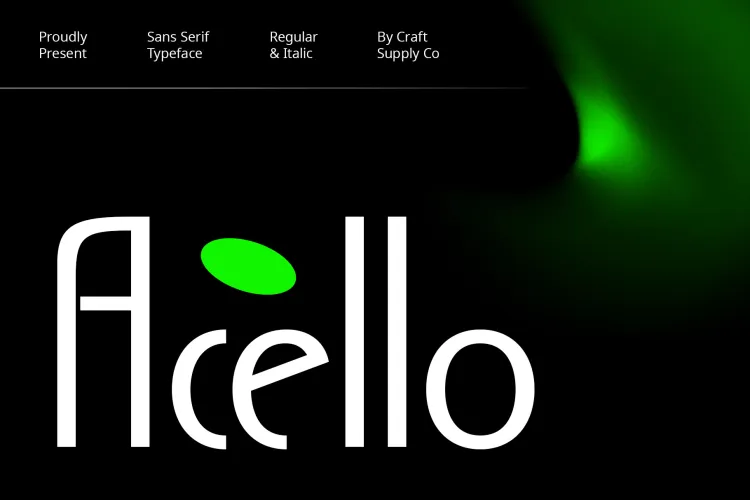
Minimalistisch und modern – klare Kreisformen und reduzierter Look.
2. Arnel – Bold Sans Serif
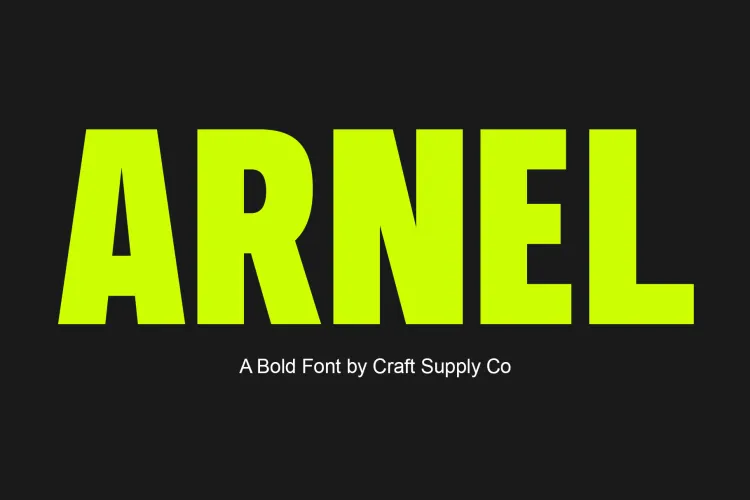
Starke Präsenz, ideal für plakative Headlines.
3. Bergins – Grotesque Sans Serif
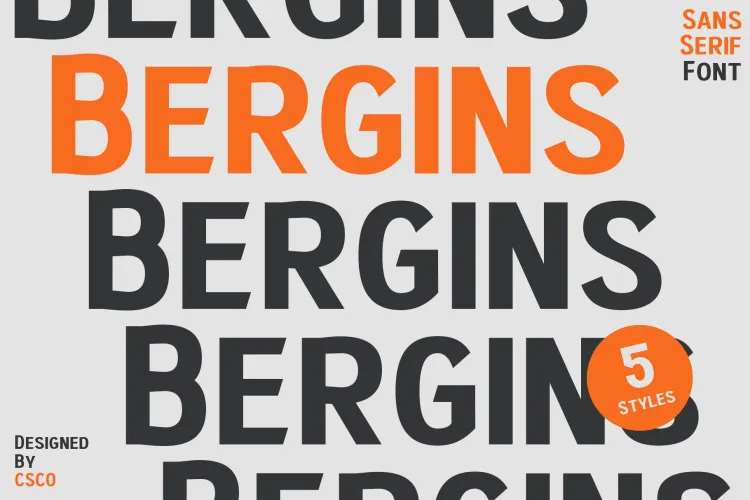
Retro-Anklänge mit zeitgemäßem Twist – vielseitig einsetzbar.
4. Blonden – Condensed Sans Serif
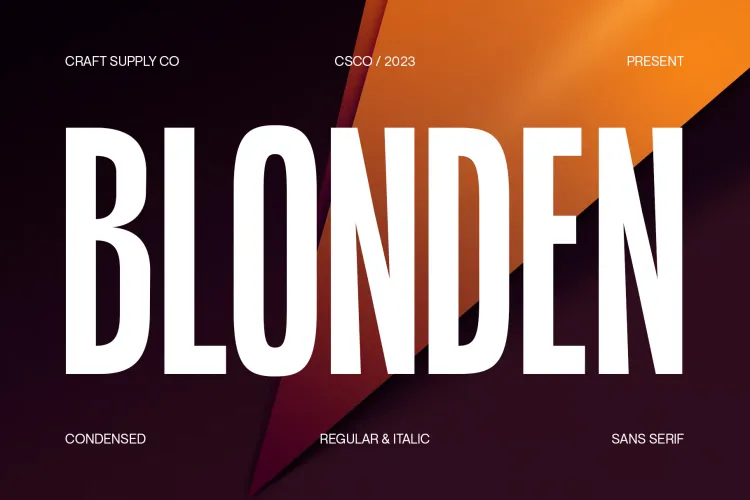
Schmal und elegant – perfekt bei wenig Platz.
5. Bondie – Condensed Sans Serif
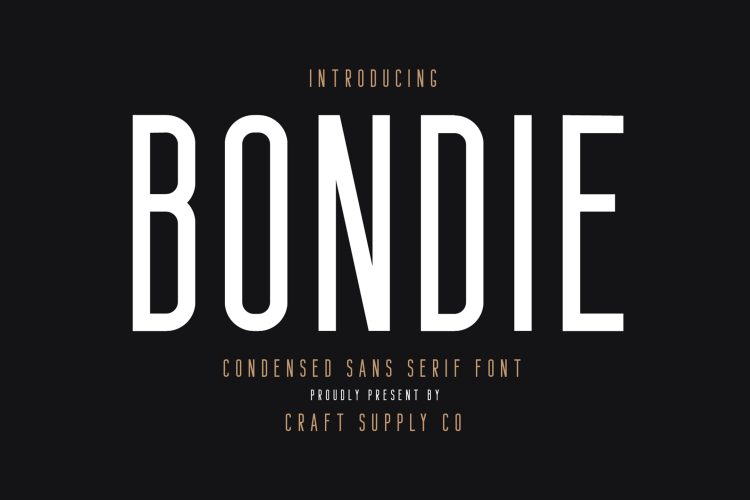
Klare Linien, optimierte Lesbarkeit – ein echter Allrounder.
6. Campeno – Geometric Sans Serif
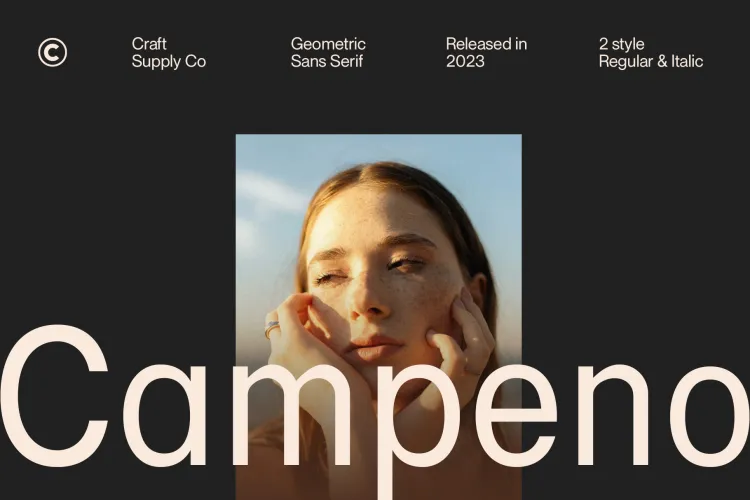
Geometrischer Charme mit moderner Note.
7. Cenios – Expanded Sans Serif
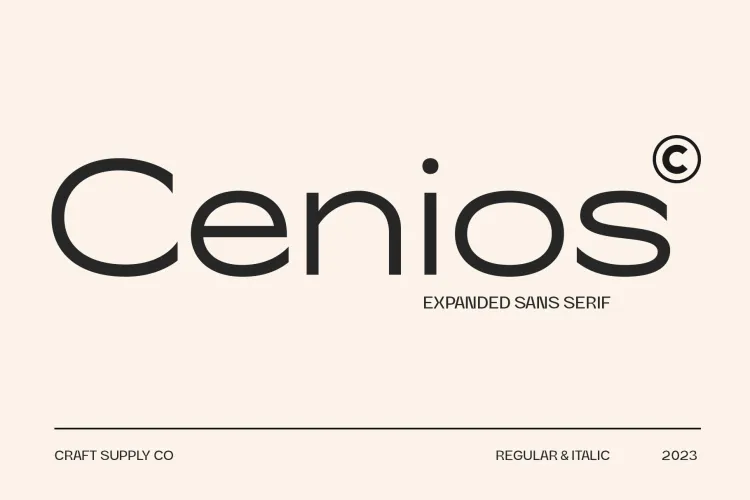
Weitläufiger Font mit großem Auftritt.
8. Corwine – Modern Font
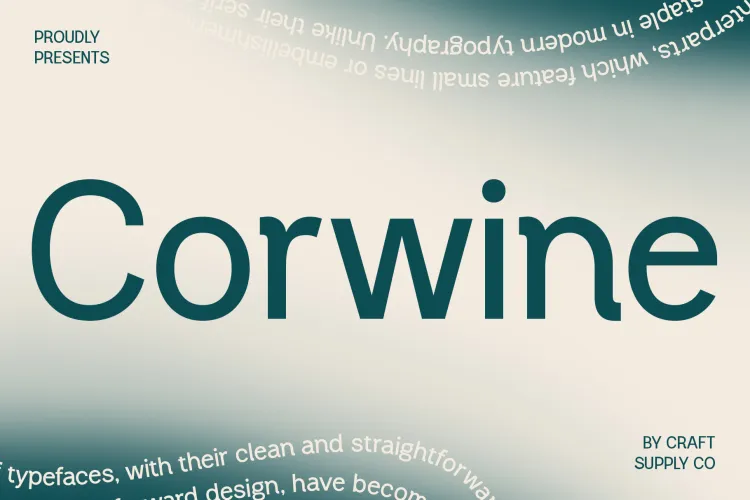
Neutraler Charakter mit zeitlosem Flair.
9. CS Margiela – Contemporary Font
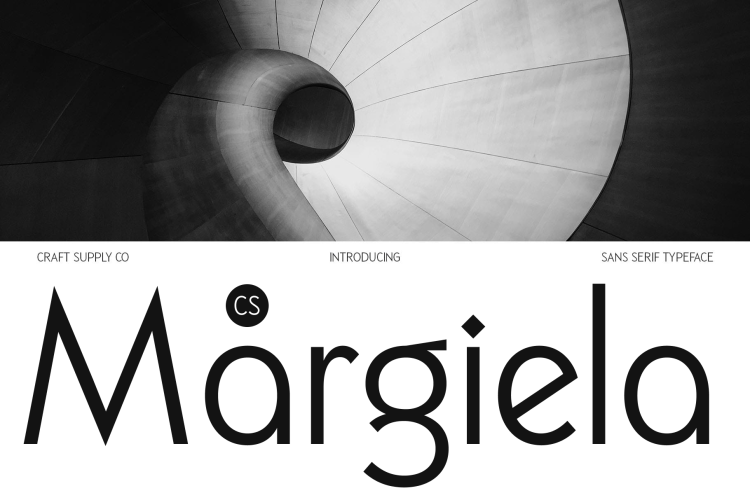
Modisches Grotesk-Design mit Coolness-Faktor.
10. CS Monica – Contemporary Font
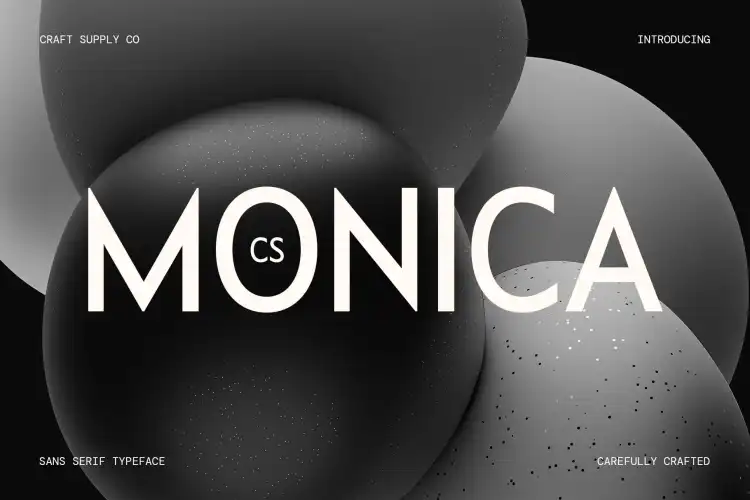
Sanfte Rundungen, humanistische Grotesk-Anmutung.
11. CS Morado – Contemporary Font
Kontrastreicher Font mit modernem Ausdruck.
12. CS Nestor – Contemporary Font
Technisch, solide – ideal für Interfaces.
13. CS Vision – Techno Font
Futuristische Anmutung: perfekt für digitale Marken.
14. Demine – Condensed Bold Sans Serif
Breit und kräftig – Headlines mit Durchschlagskraft.
15. Dozed – Condensed Sans Serif
Effizient und kompakt – für klare Layouts.
16. Godger – Condensed Sans Serif
Stabilität trifft auf schmale Eleganz.
17. Impana – Modern Sans Serif
Zeitgemäß und vielseitig – für Web- und Print.
18. Kalesi – Elegant Sans Serif
Fein austariert, feminin und modern.
19. Mikea – Elegant Luxury Font
Luxuriös, high-end und dennoch schlicht.
20. Robine – Condensed Sans Serif
Effizient, nüchtern, edel.